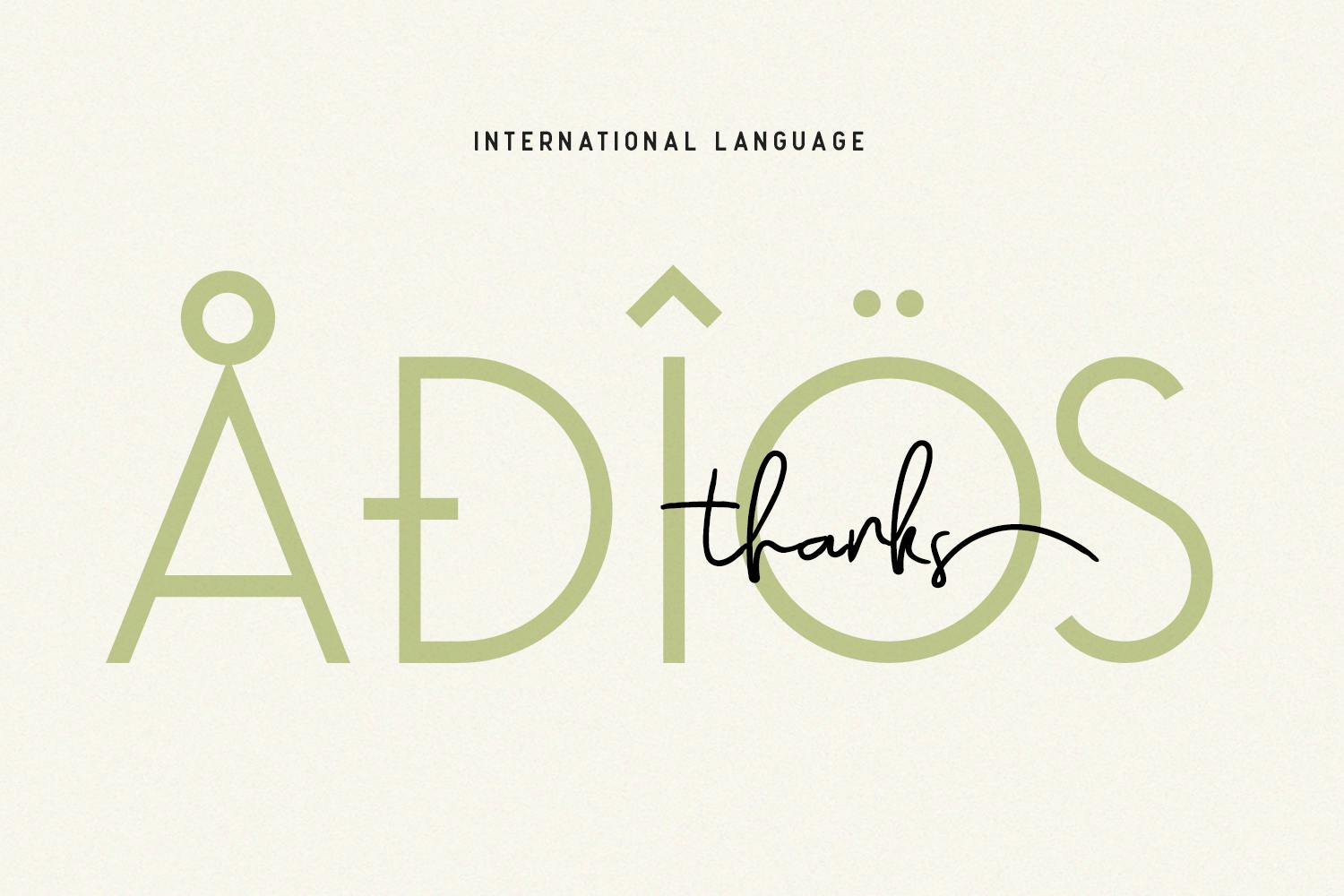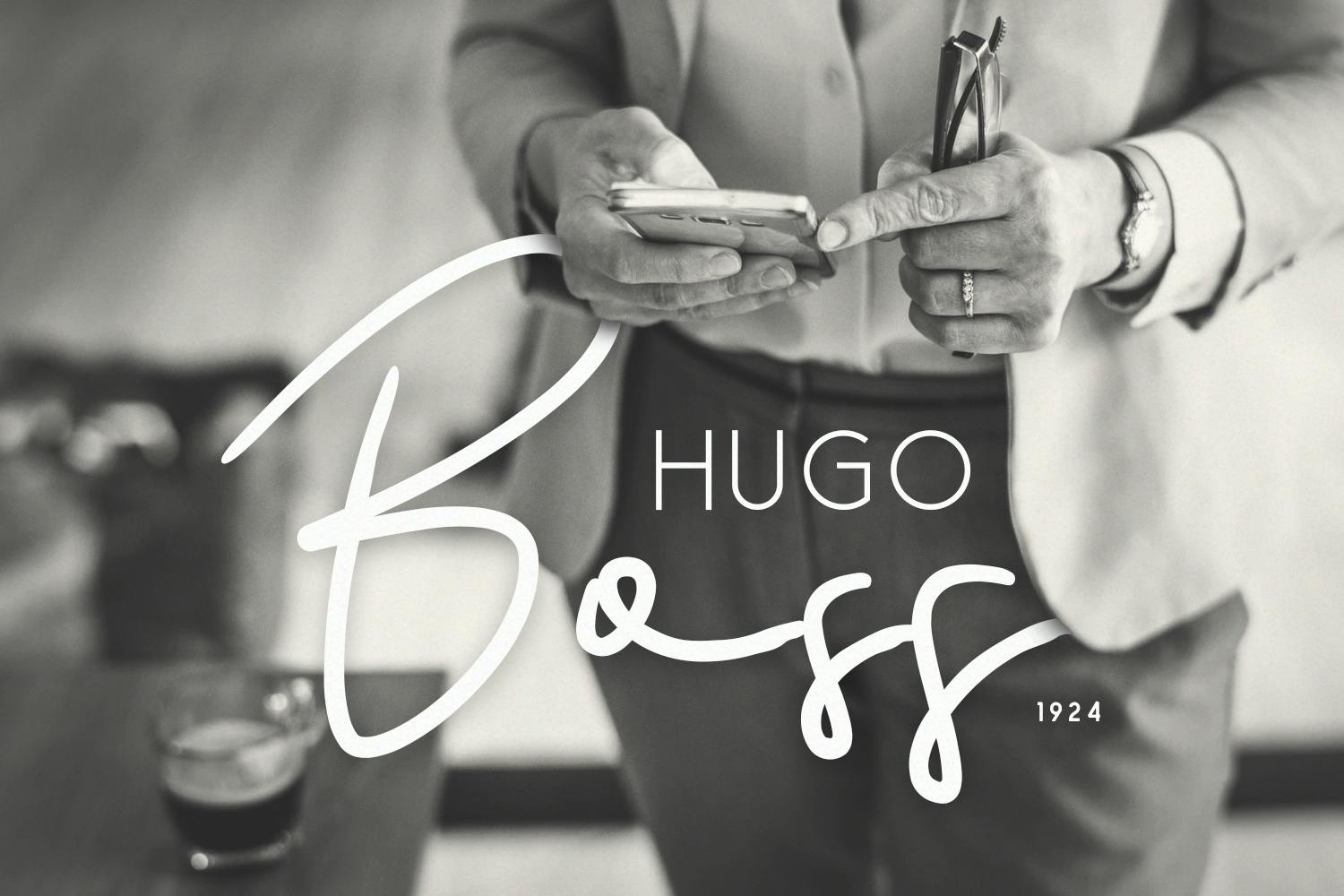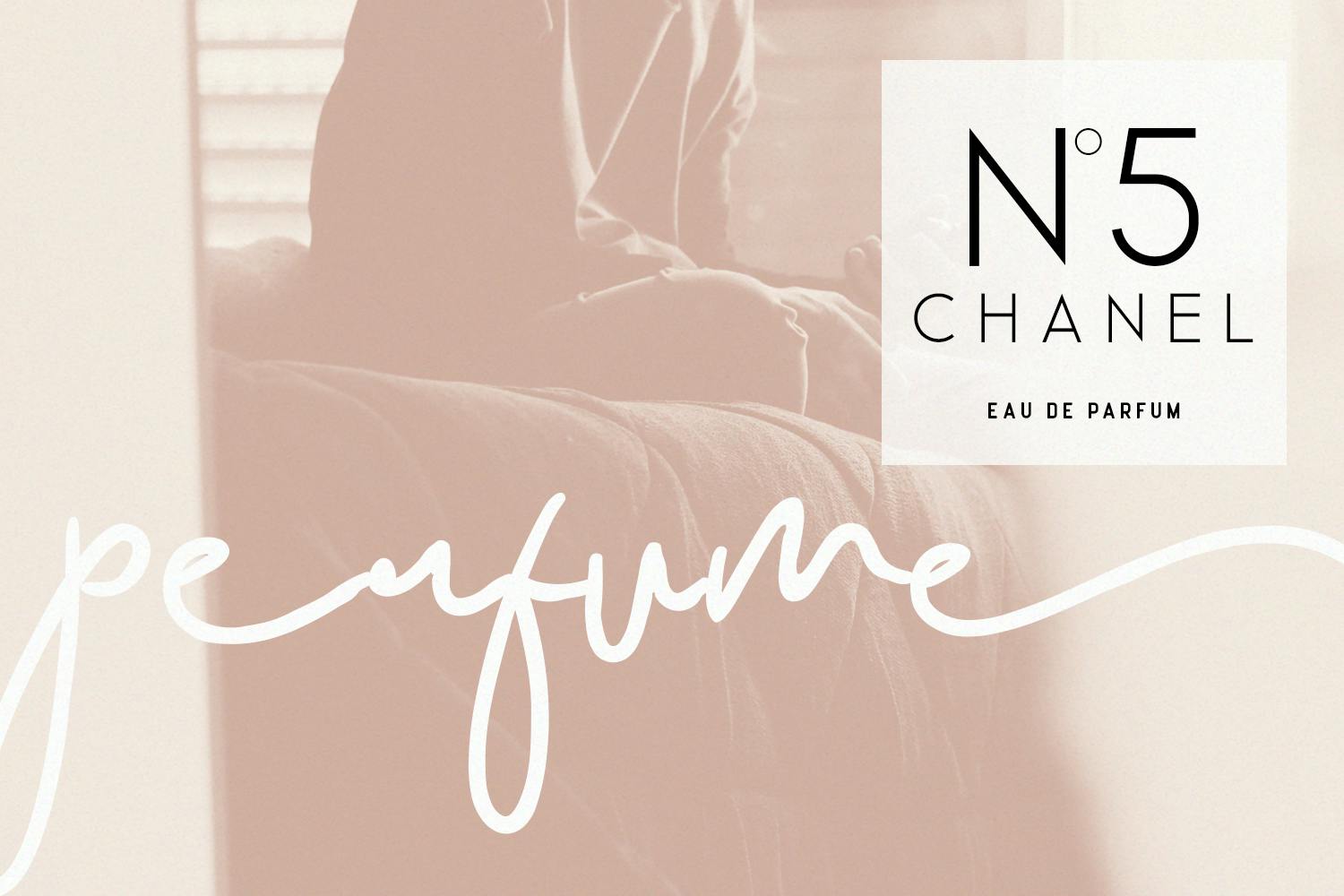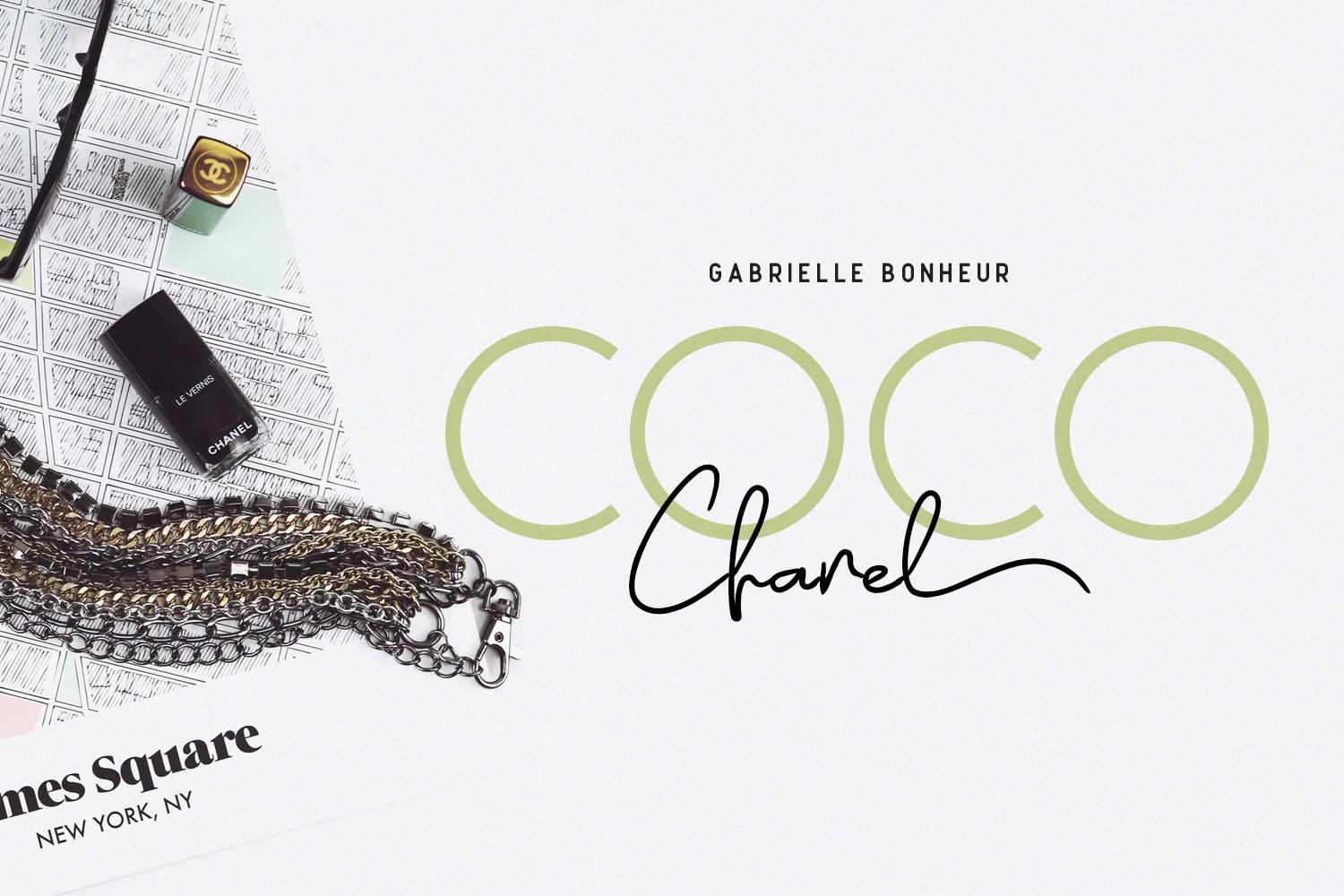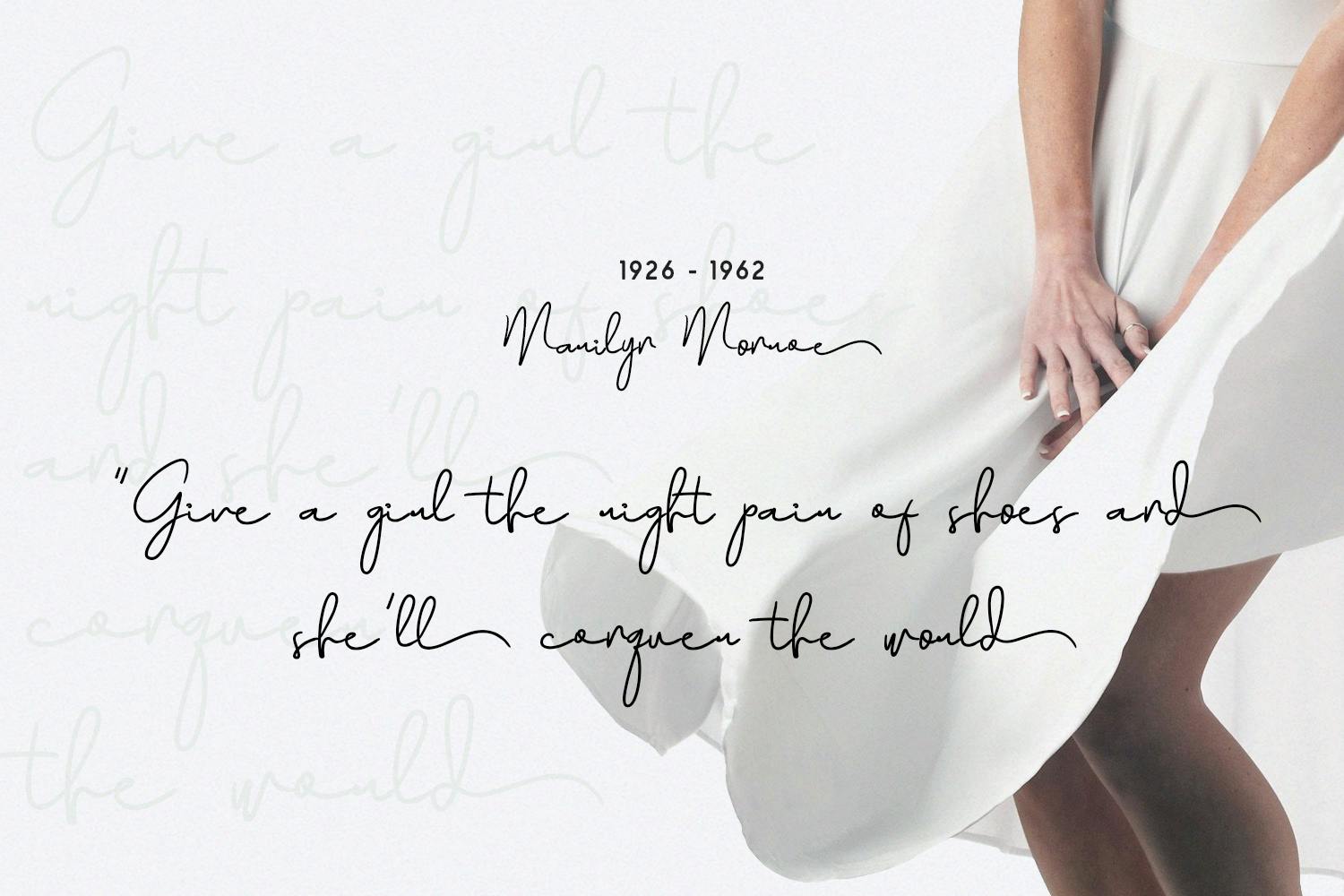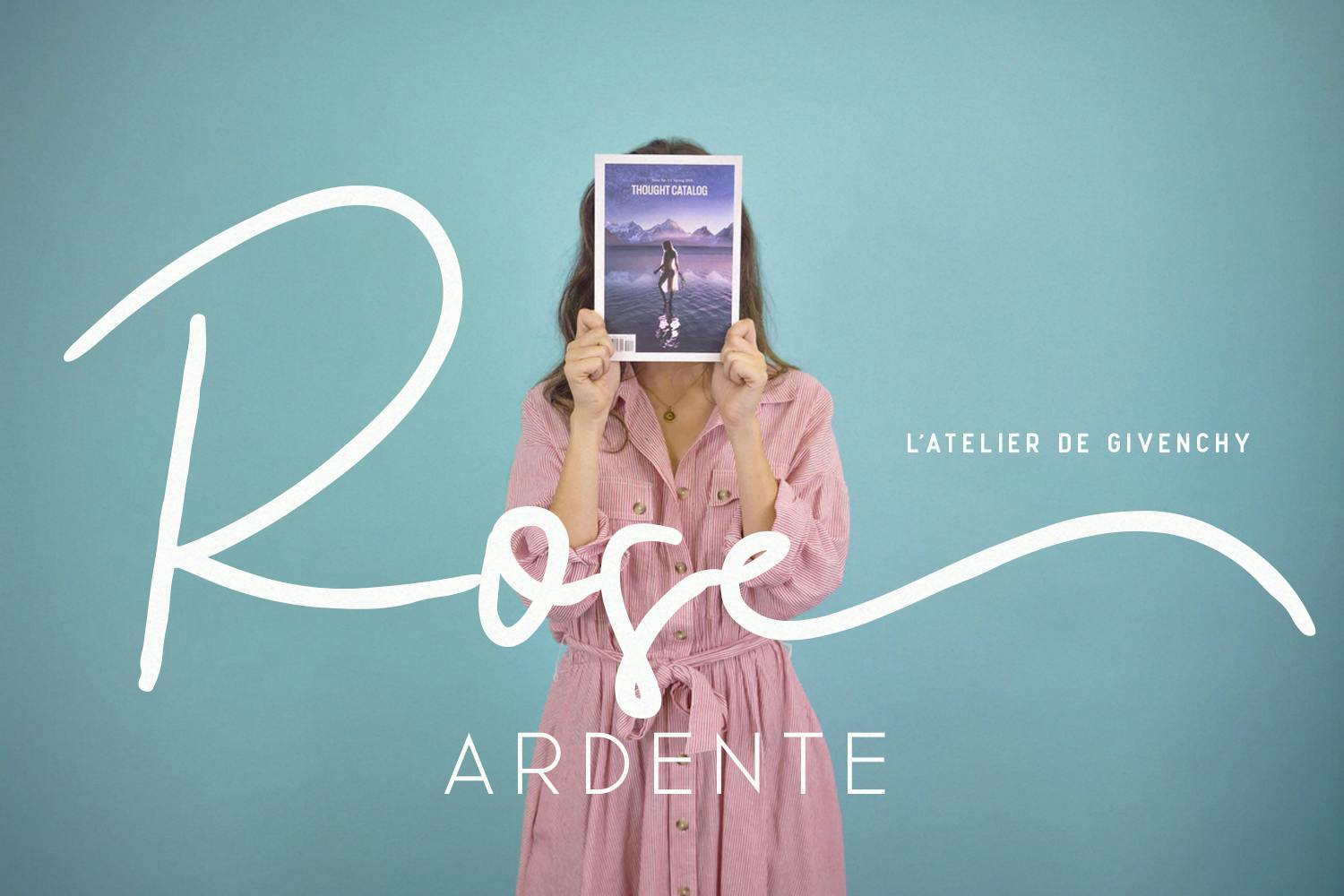
فونت مایا لوکس - Maya Luxury Signature Font یک مجموعه مدرن از فونتهای اسکریپت و سنس-سریف است. این فونتها هماهنگی زیبای تایپوگرافی را برای پروژههای طراحی متنوع، عنوانها، برندینگ، هویت بصری، پوسترها، لوگوها، مجلات و غیره ارائه میدهند.